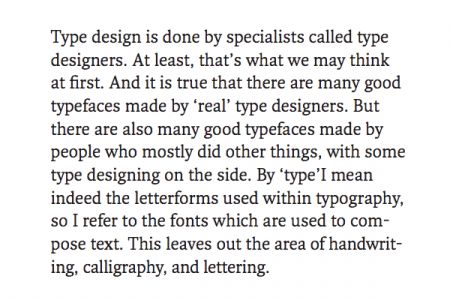
Habe mich in die »Fresco« verliebt
ich habe mich total in die »Fresco« von OurType.be verliebt. Allerdings kann ich mir das komplette Paket als Student nicht leisten.
Trotzdessen hätte ich gern eine Brotschrift mit ähnlicher Anmutung für meine Diplomarbeit. Gleichzeitig suche ich eine dazu passende Grotesk,
die ruhig auch etwas experimentell in den Ligaturen sein darf.
Könnt ihr mir weiterhelfen?
Abgesehen davon, bleibt immer noch die Frage nach einer passenden Grotesk.
Myriad Pro würde sicherlich passen, ist mir aber etwas zu »schüchtern«.
Doch nun mal zur zweiten Frage. Einer Grotesk für die Überschriften passend zur »Fresco«.
Ich hänge auch mal einen Screenshot aus der Specimen-PDF an, so daß ihr seht, wie die »Fresco« überhaupt aussieht.
Es geht in der Arbeit schon um Typographie. Aus diesem Grund und meinem persönlichen Geschmack
empfinde ich FF Bau, Syntax und auch Auto als zu brav. Mein Satzspiegel wird so gestaltet sein,
daß die Überschriften ruhig etwas aus der Reihe tanzen dürfen. Damit spreche ich den oben genannten
drei Schriften natürlich nicht ab, daß sie sehr gut zur »Fresco« passen würden.
Sind halt nur noch nicht so ganz das, was ich suche.
Da hast du ja wirklich die »elegantesten« Sans-Serif-Schriften von emigre rausgesucht Typografski.
Wobei mir die PRIORI zu uneinheitlich in ihren »Allüren« ist. Die Vista dafür wieder etwas zu brav.
Bei Fountain.nu gibt's zwei schöne Kandidaten:
Mercury (http://www.fountain.nu/catalogue/mercury_reg.asp)
Lisboa (http://www.fountain.nu/catalogue/lisboa.asp)
Bei der Lisboa gefallen mir vor allem die Anstriche und Ligaturen. Sehr schick in meinen Augen.
Würde die denn passen?
ich find beide fonts eigentlich zu verspielt um sie mit
der eh schon "verspielten" fresco zu kombinieren ...
ich wuerde auch eher zu etwas neutralerem tendieren.
oder probiers doch mal direkt mit der fresco sans.
Eigentlich hast du recht Microboy. Die »Fresco« ist ja wirklich wunderbar ausgebaut und
wenn es gleich eine Sans-Serif dazu gibt, warum nicht die nehmen :D
Hab das gerade mal mit dem wirklich sehr gelungenen Flash-basierten Probetool von OurType probiert.